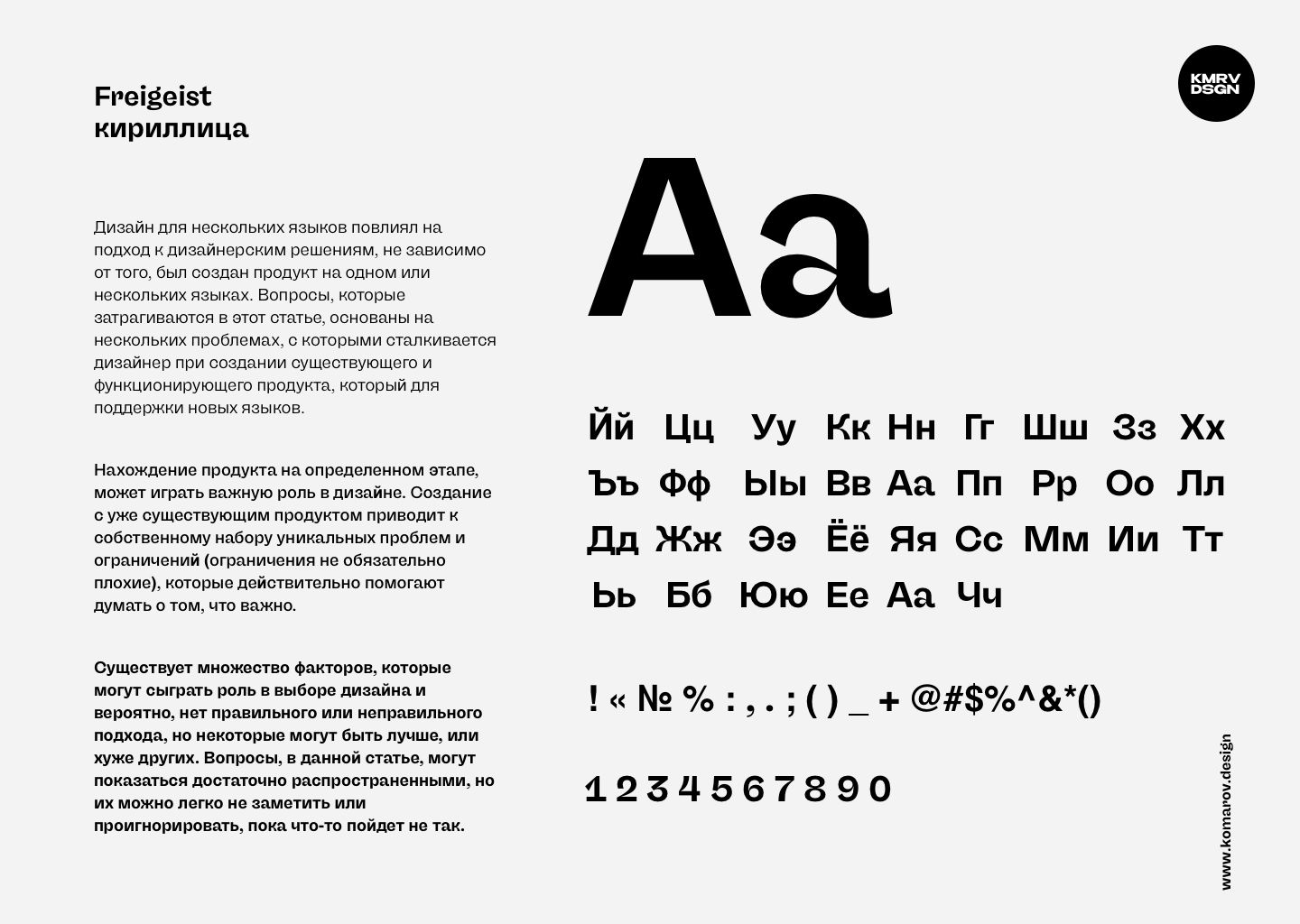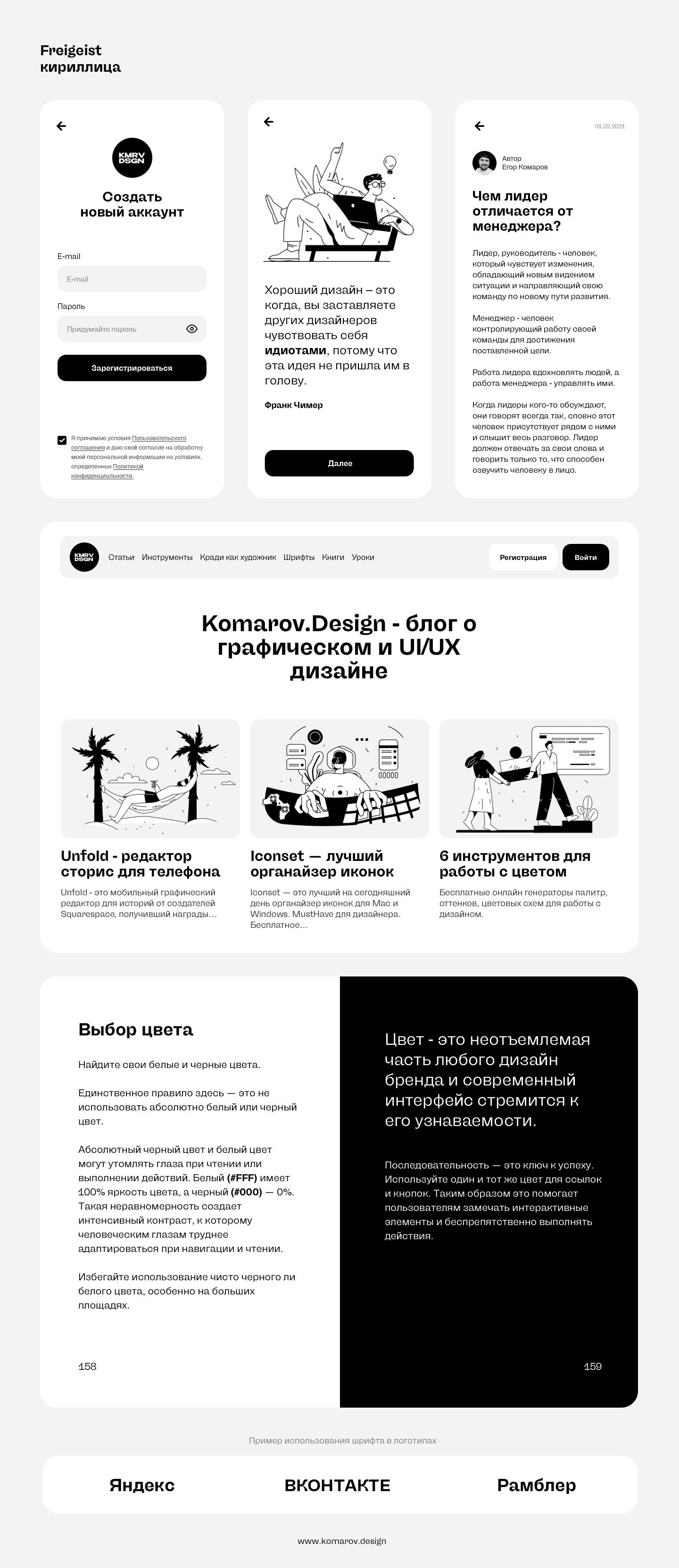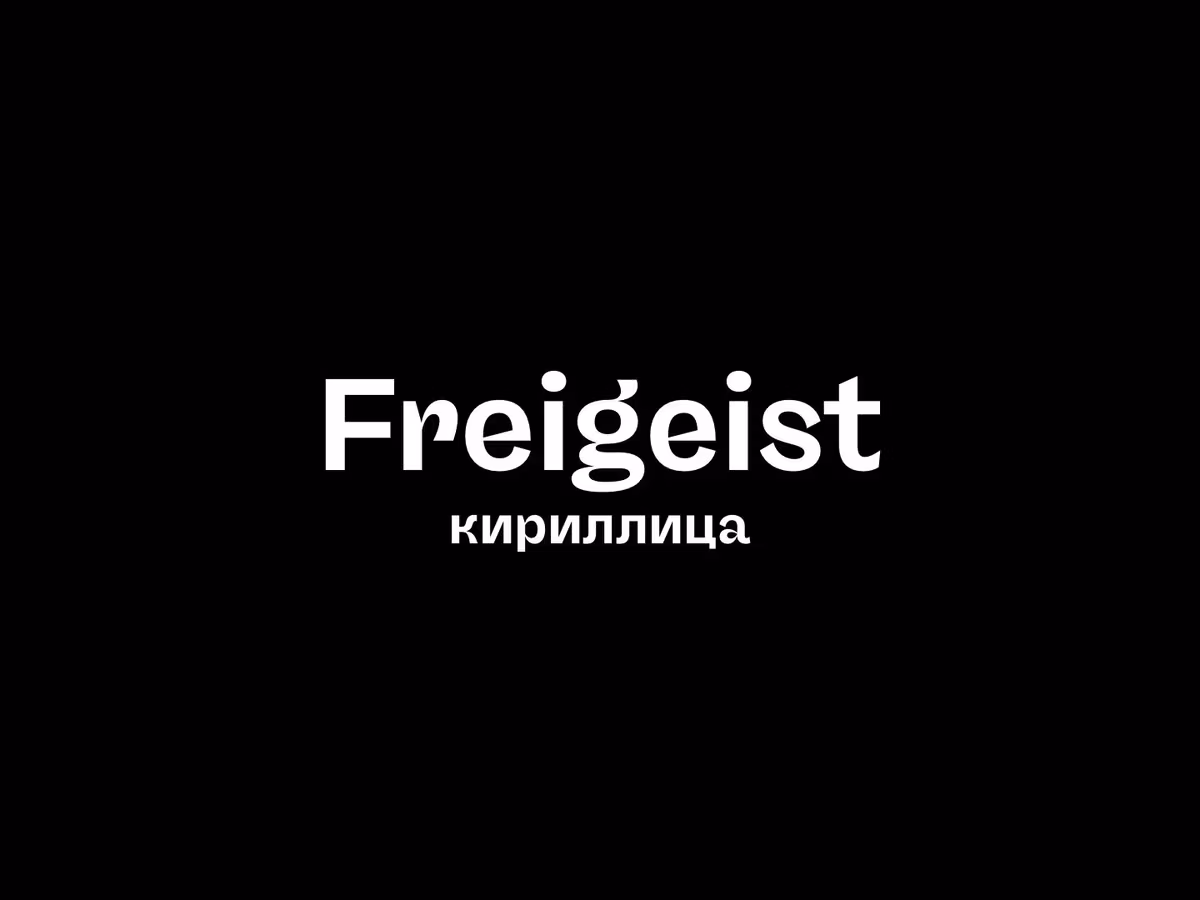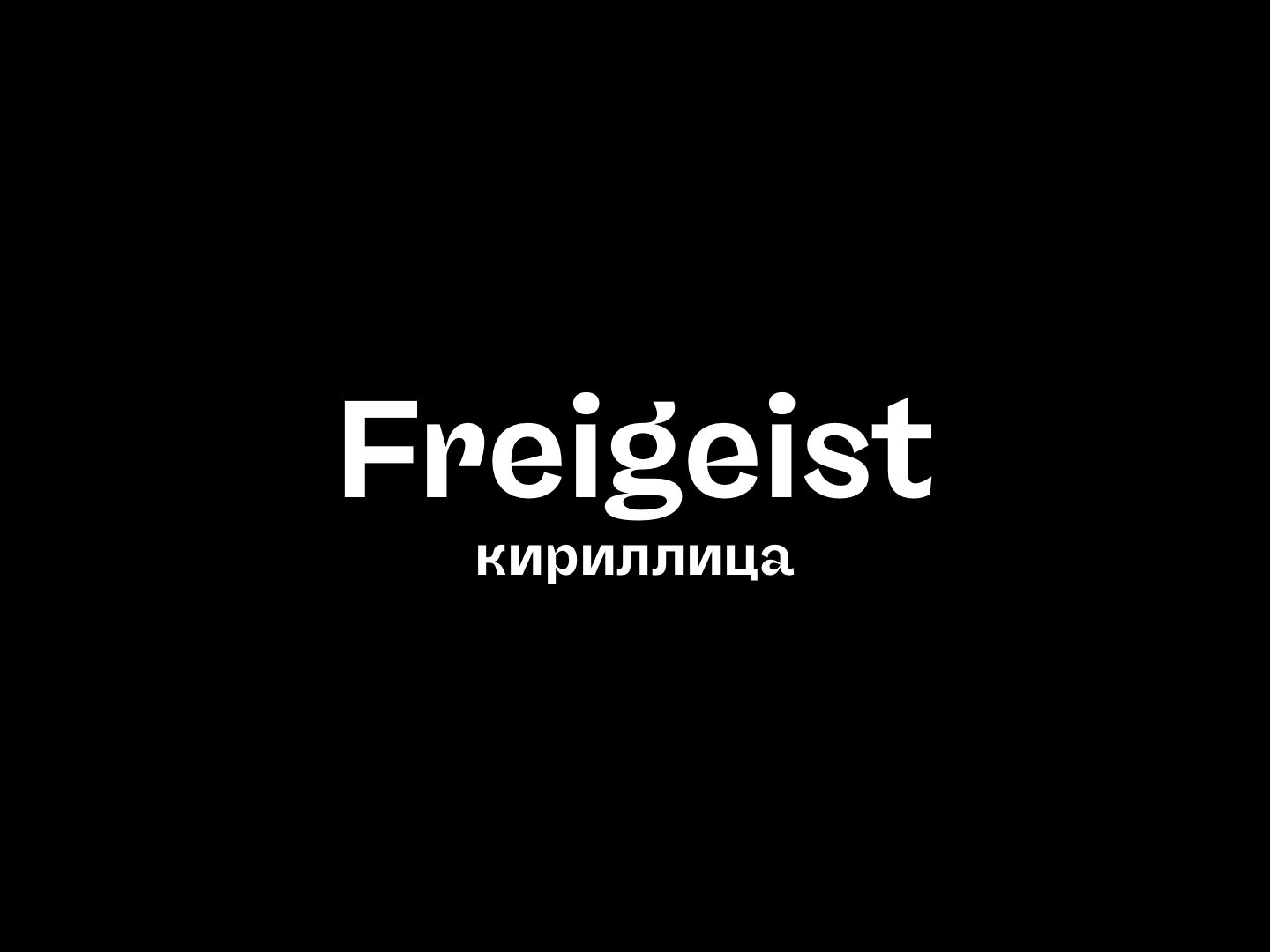
Freigeist шрифт
Freigeist - это суперсемейство кириллических гротесков. Он отражает неприрученный и выразительный дух ранних шрифтов без засечек 19 века и помещает их в современный контекст, в результате чего получается многогранное семейство с широким спектром стилей шрифтов и функций для современного набора.
Freigeist - это суперсемейство кириллических гротесков, имеющее 6 значений ширины и 6 толщин плюс соответствующий курсив. Он отражает неприрученный и выразительный дух ранних шрифтов без засечек 19 века и помещает их в современный контекст, в результате чего получается многогранное семейство с широким спектром стилей шрифтов и функций для современного набора. Семейство недавно получило огромное обновление дизайна и технических характеристик, теперь оно доступно в версии 2.0 и имеет моноширинную ширину.